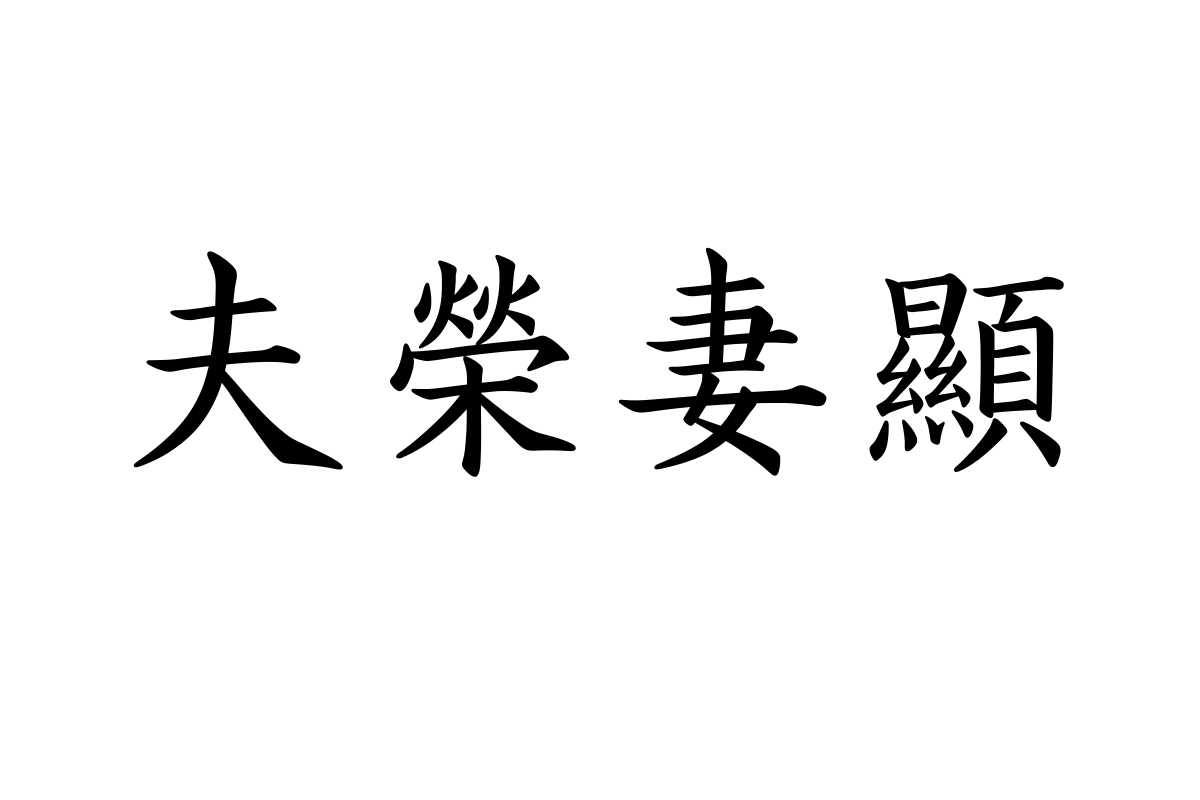
汉仪全唐诗繁体字体是一款专为中文排版设计的字体,适用于各类中文出版物,如书籍、杂志、报纸等。该字体具有以下特点:
1. 字形美观:汉仪全唐诗繁体字体的字形结构严谨,线条流畅,整体视觉效果优美。
2. 字重清晰:该字体的字重适中,既有楷书的规整感,又有行书的灵动性,适合阅读和书写。
总之,汉仪全唐诗繁体字体是一款功能强大、使用广泛的中文排版字体,适用于各类中文出版物的设计与制作。